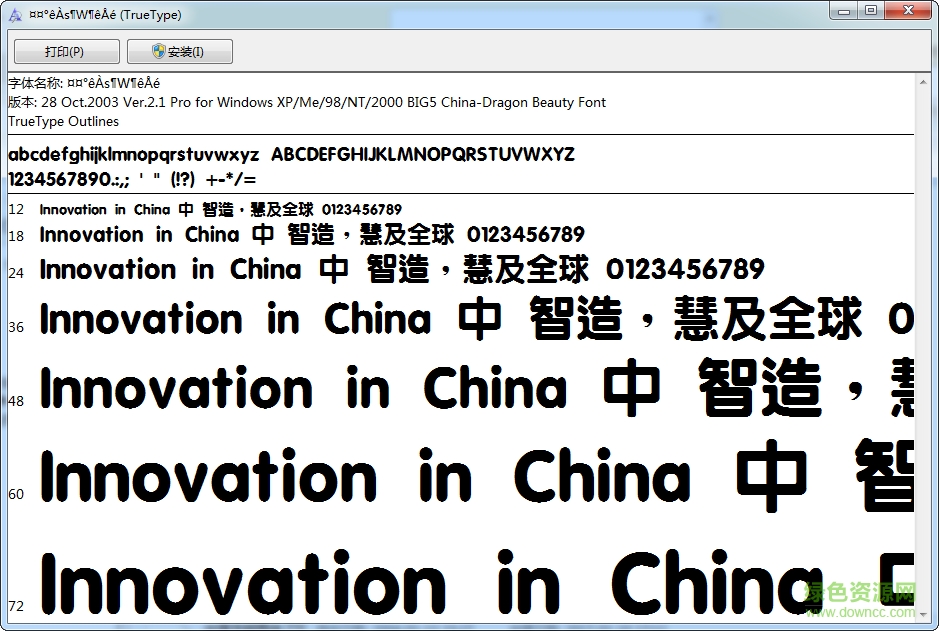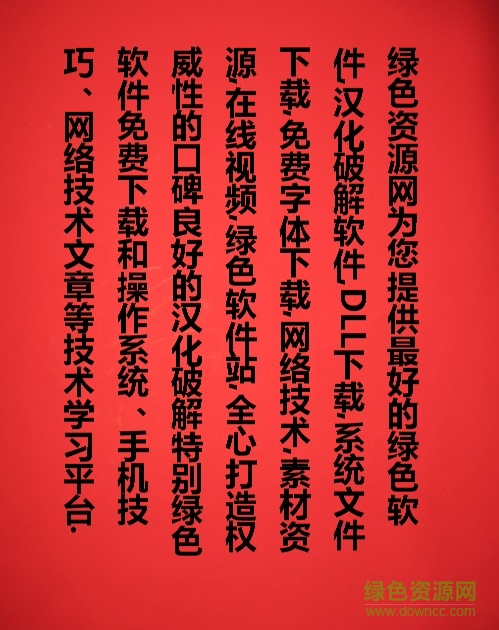
中國龍超圓體是一款繁體字體。大大方方的模板讓你的字體更顯清新簡潔魅力,適合廣告設(shè)計(jì)、文字排版等行業(yè),文字看起來十分的大氣簡單,效果十分的不錯(cuò),需要的朋友請(qǐng)來綠色資源網(wǎng)你下載吧!
字體神采俊俏,雄渾中流露天真稚拙,典雅中蘊(yùn)含時(shí)代風(fēng)
采,靜中寓動(dòng)、穩(wěn)中求險(xiǎn)、巧拙相生、變化自然,結(jié)構(gòu)嚴(yán)
謹(jǐn),筆法古樸典雅,又極富裝飾意趣。適用于書籍、報(bào)
刊、雜志及各類印刷品的標(biāo)題字或裝飾用字。
字體樸實(shí)端正,筆法舒展有力,流暢自然,結(jié)構(gòu)勻稱,適
用于書、報(bào)、雜志和各級(jí)教材中的小標(biāo)題及正文字